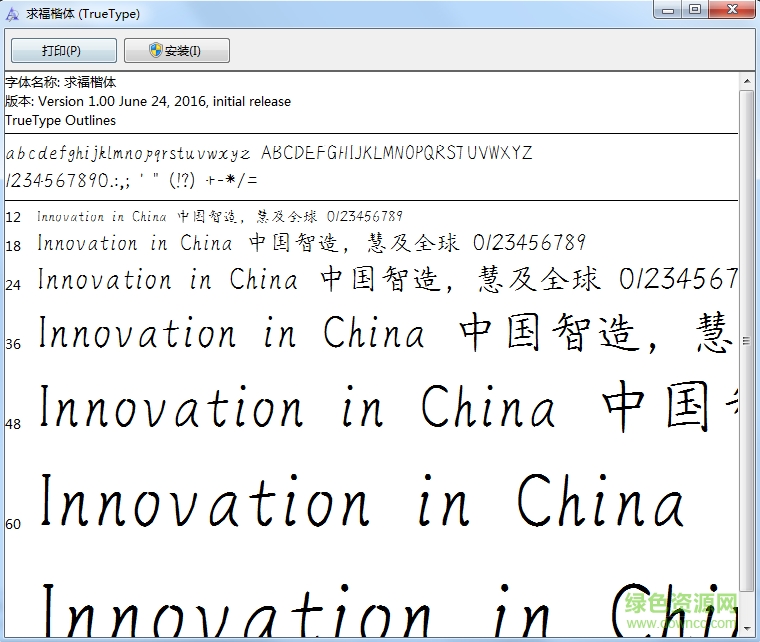
求??w是一款清爽干凈的方正字體,端正的楷書字體格式,感受最簡(jiǎn)約最清新的視覺呈現(xiàn),無(wú)論是中文漢字還是英文字母都別有風(fēng)趣,喜歡的朋友快來(lái)綠色資源網(wǎng)免費(fèi)下載吧!
方正求??w端莊秀麗,有著“祈福求愿”的美好寓意!
讓大家在輸入時(shí)能感受安然生活的美好!